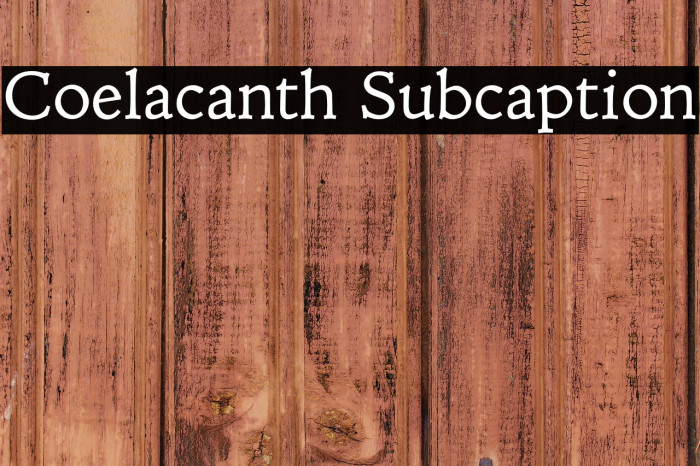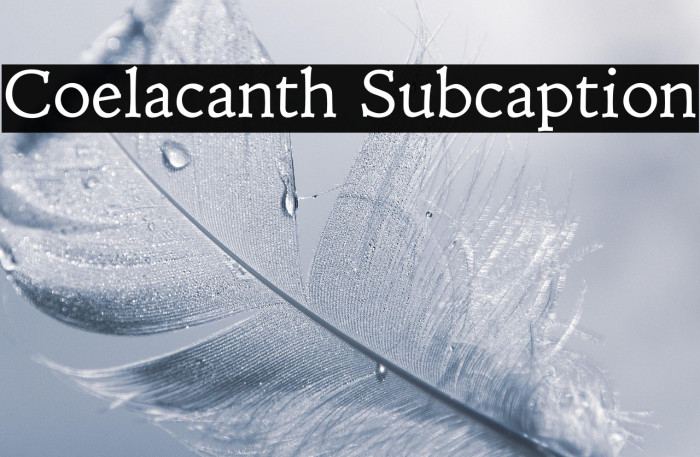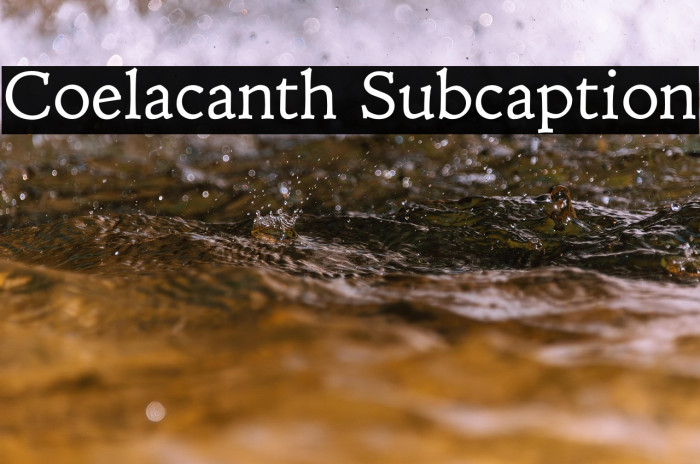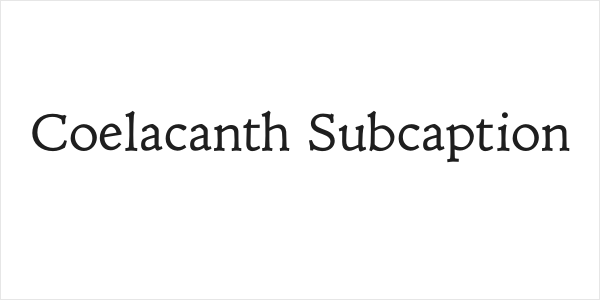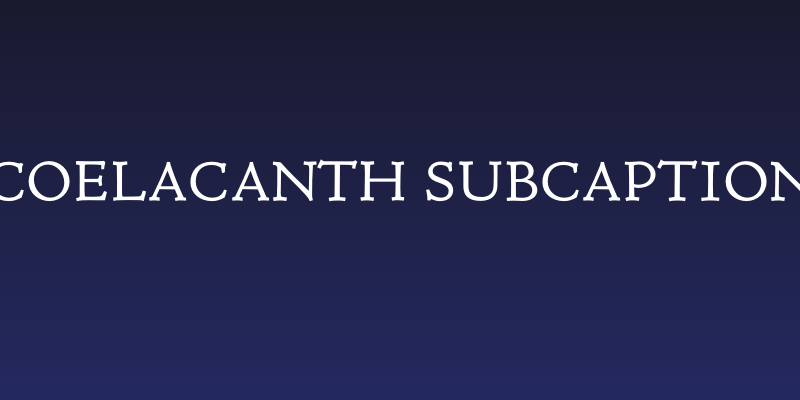
Coelacanth Subcaption Font
| Nume | Coelacanth Subcaption |
| Proiecte propuse | Ideal for editorial design, book covers, formal invitations, and branding projects that require a touch of sophistication. |